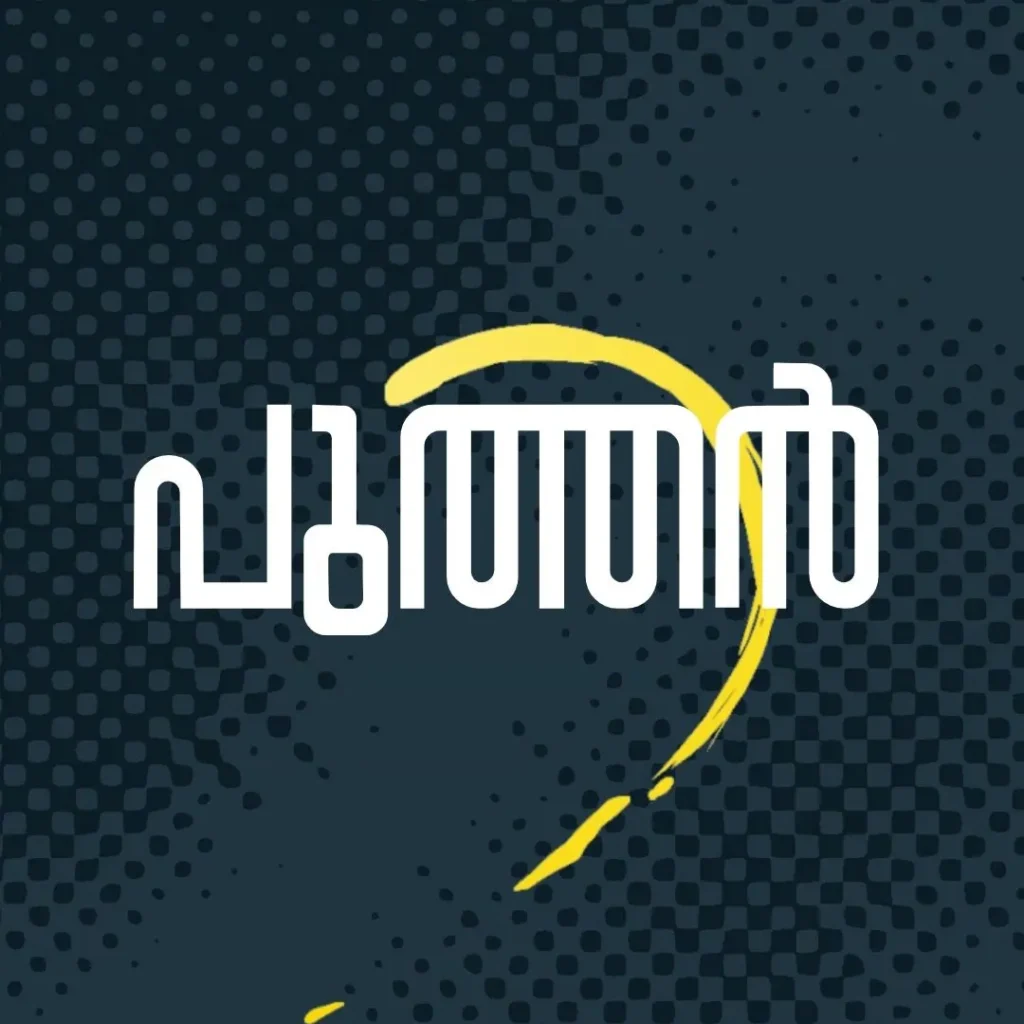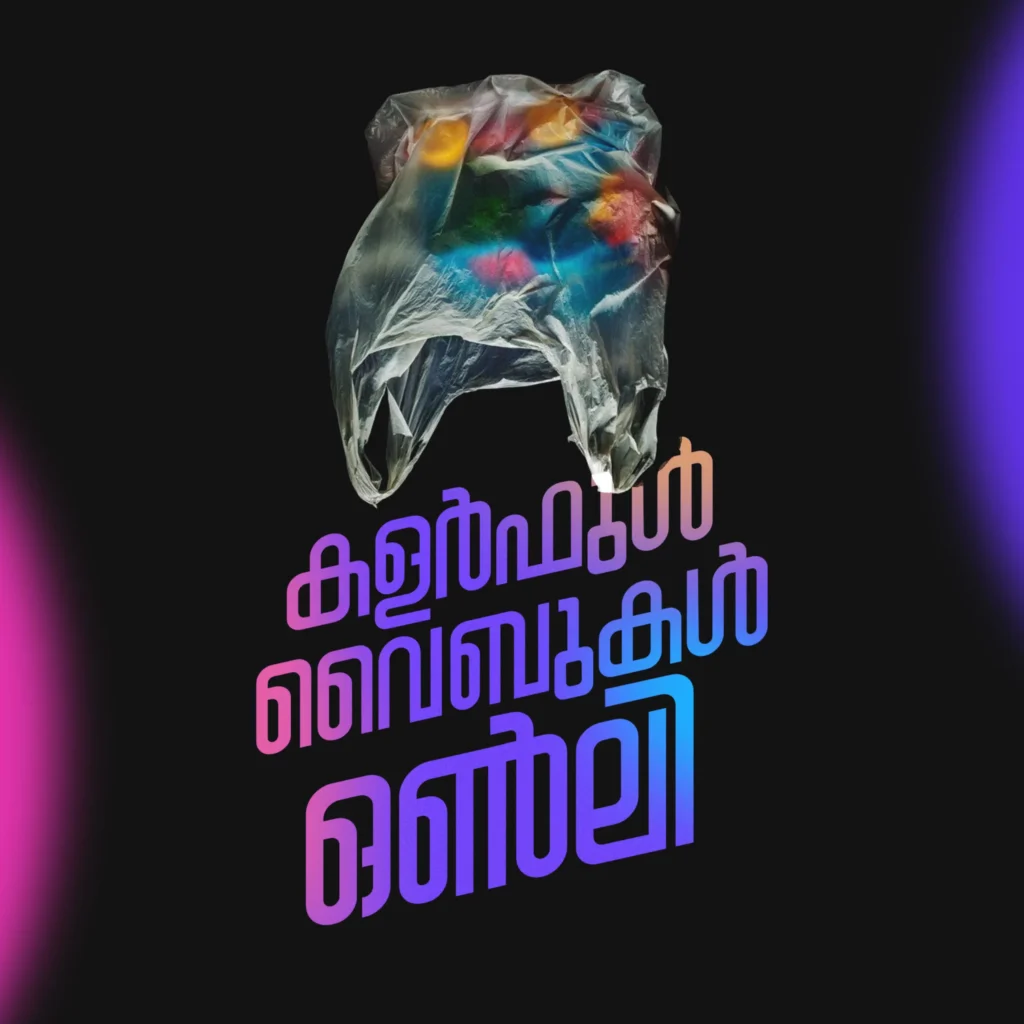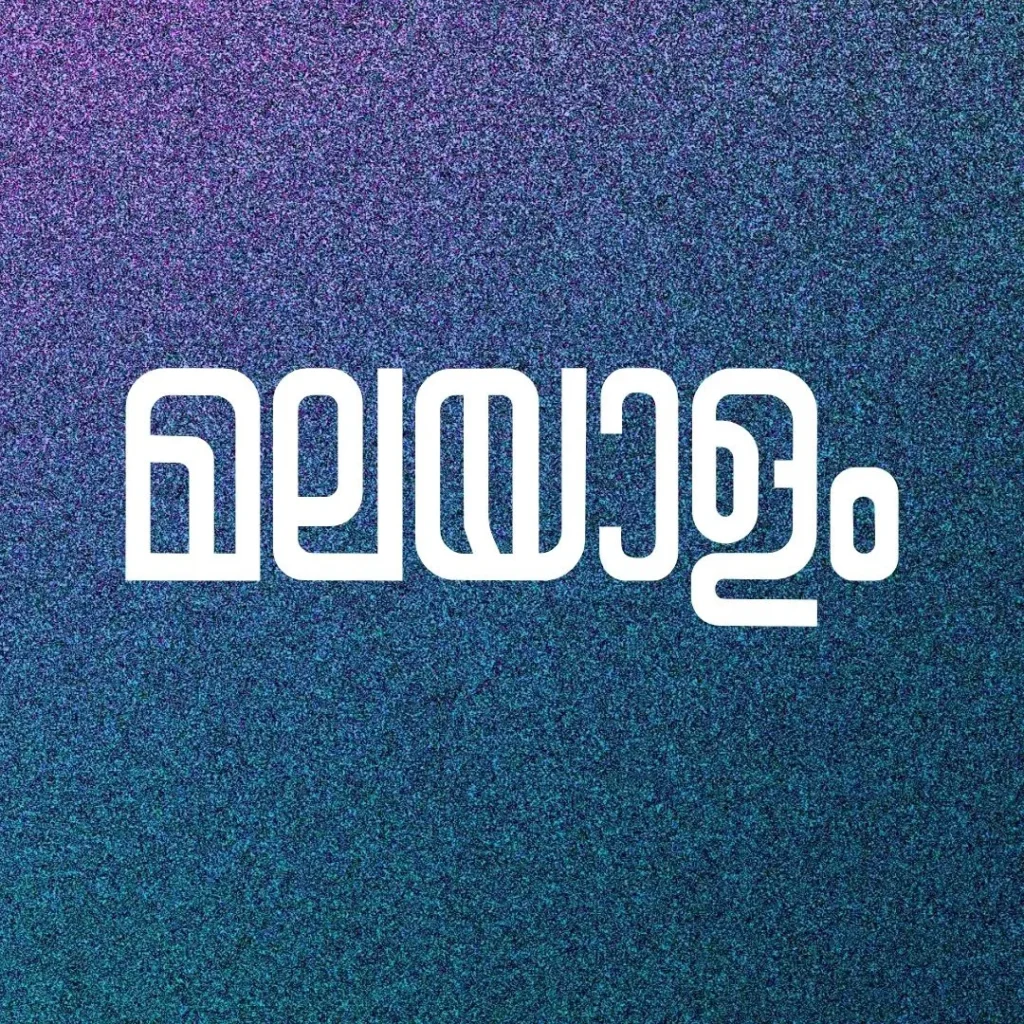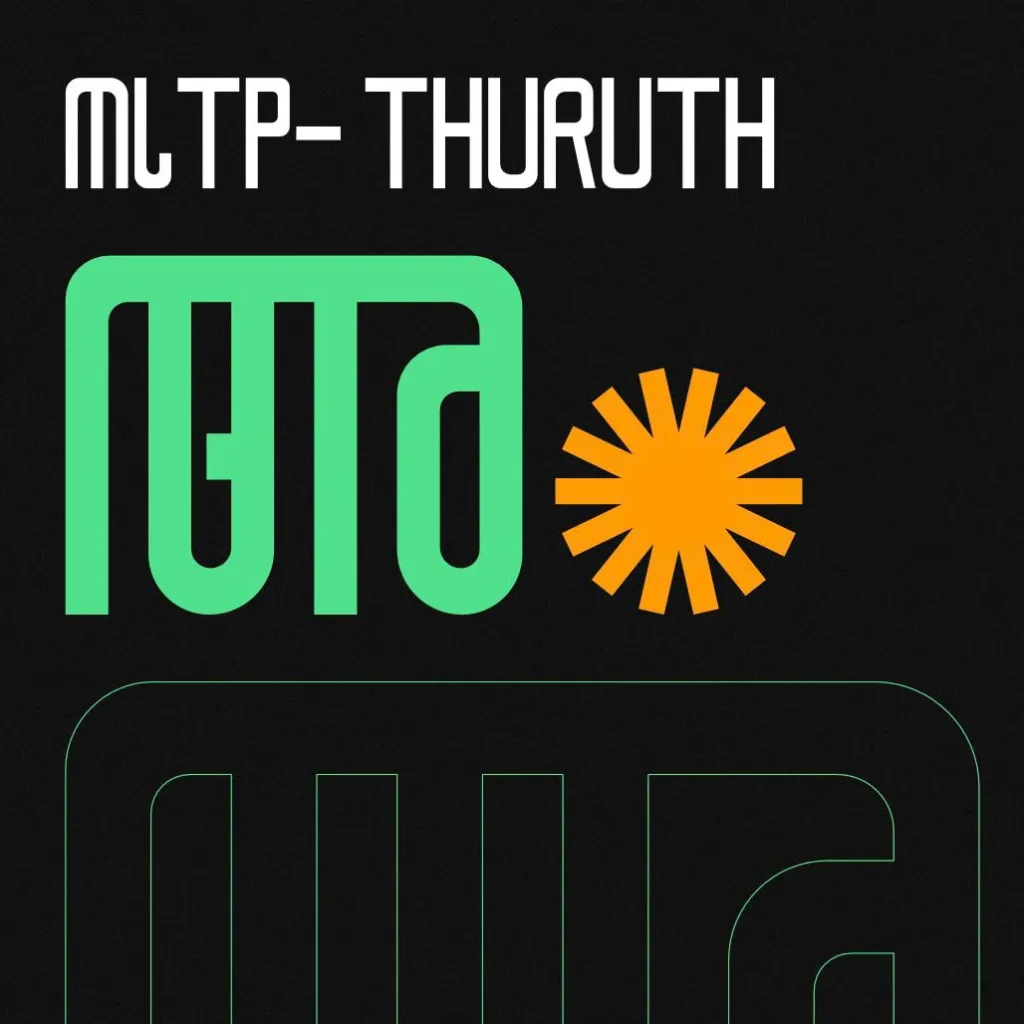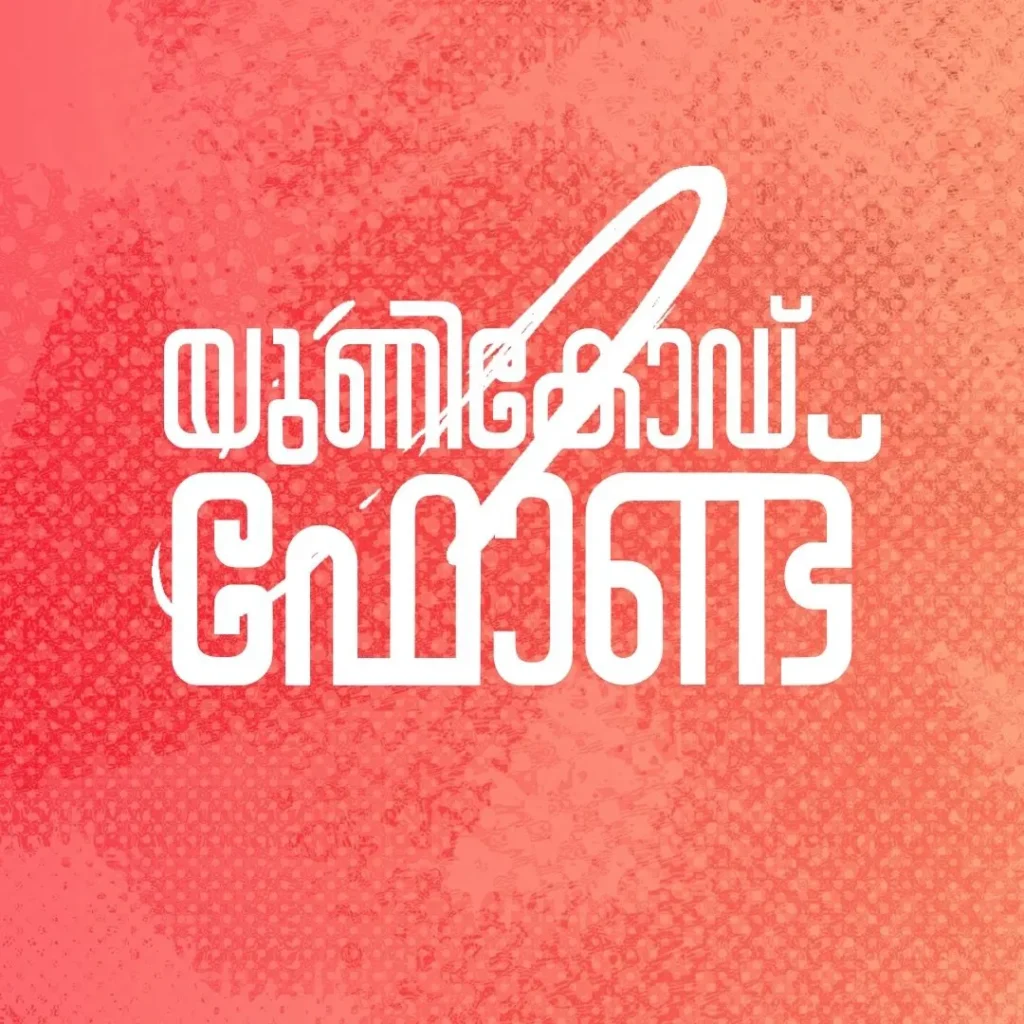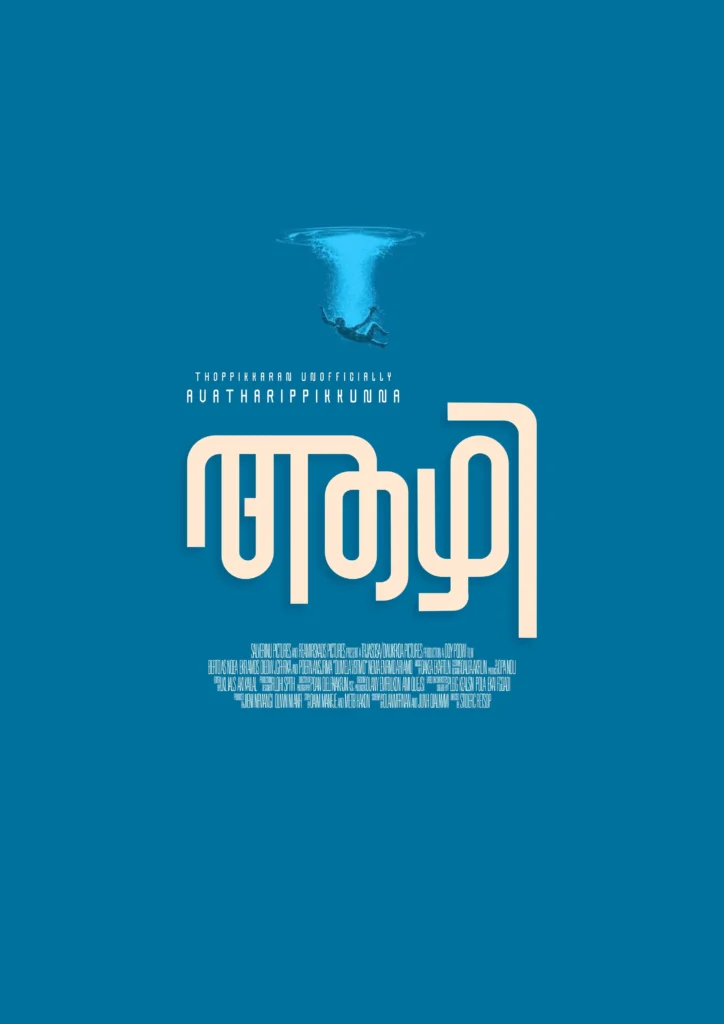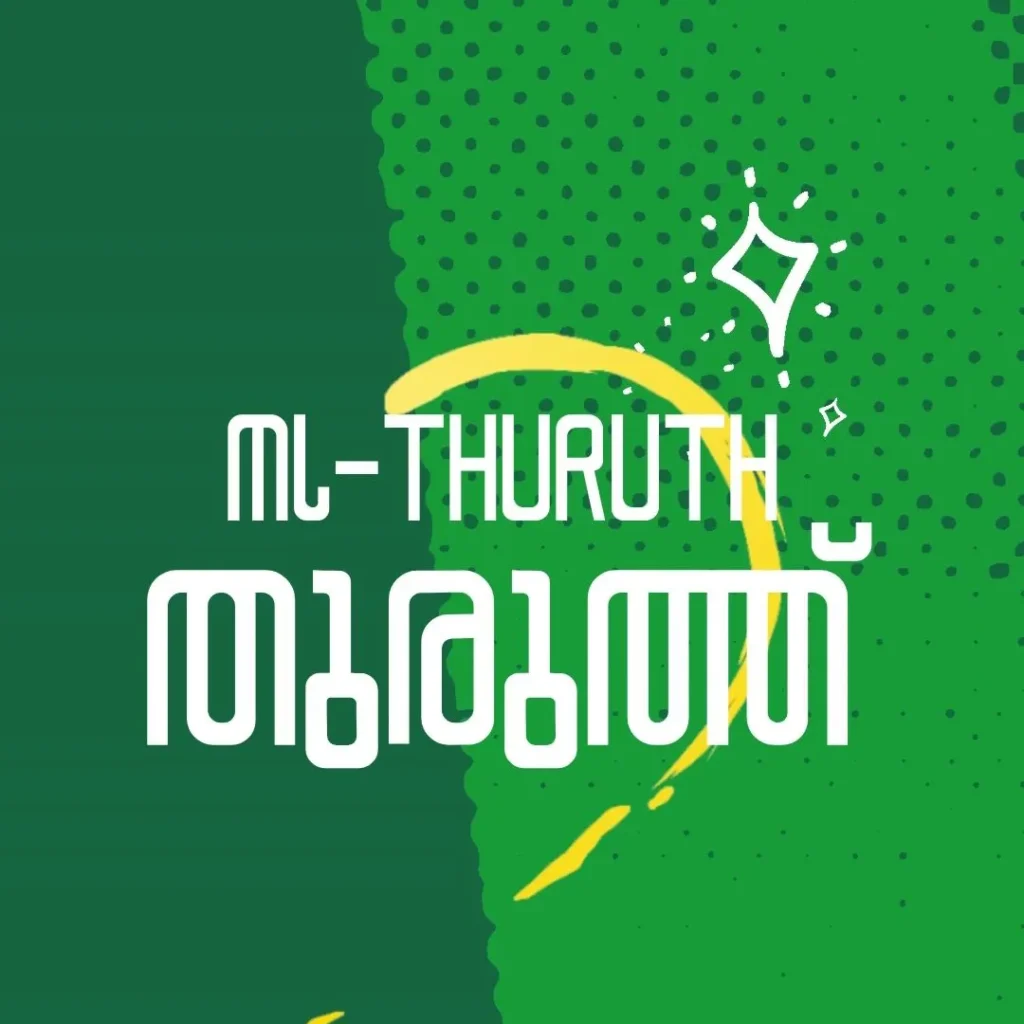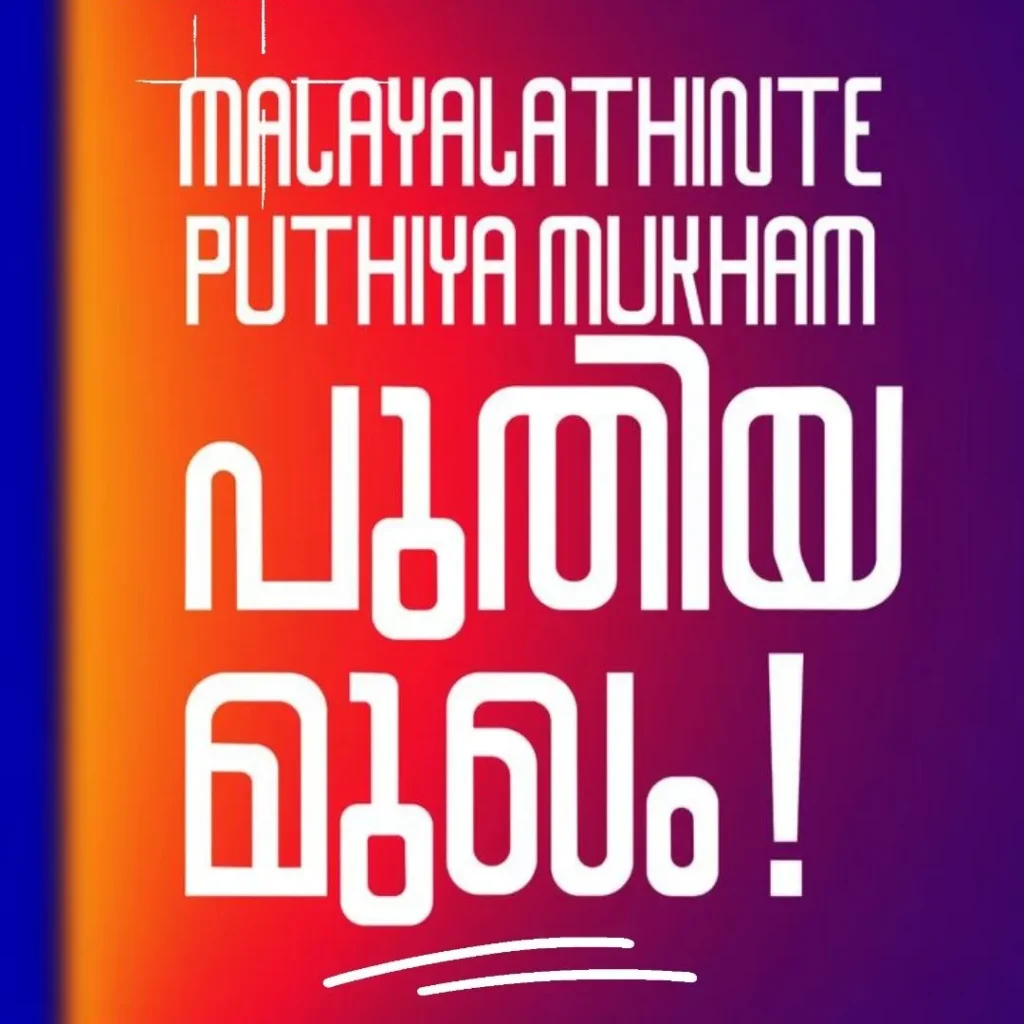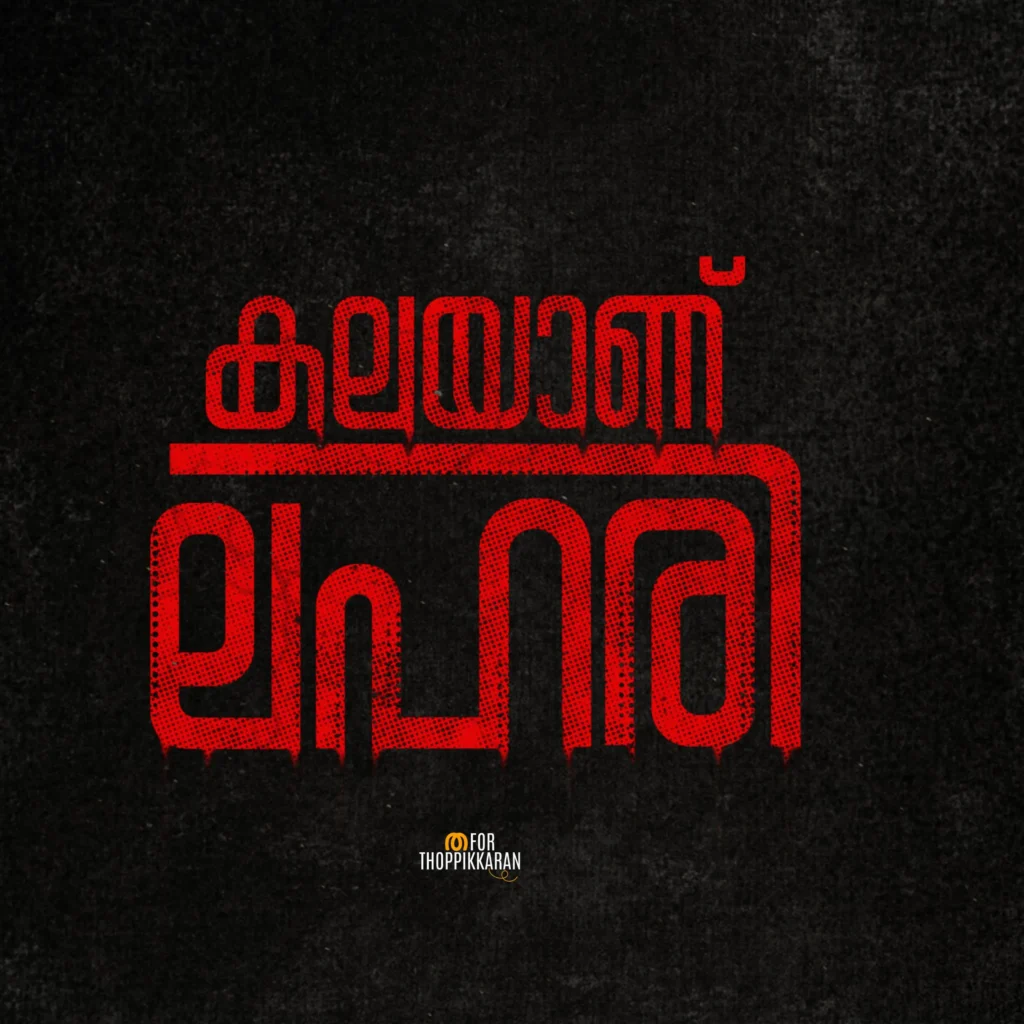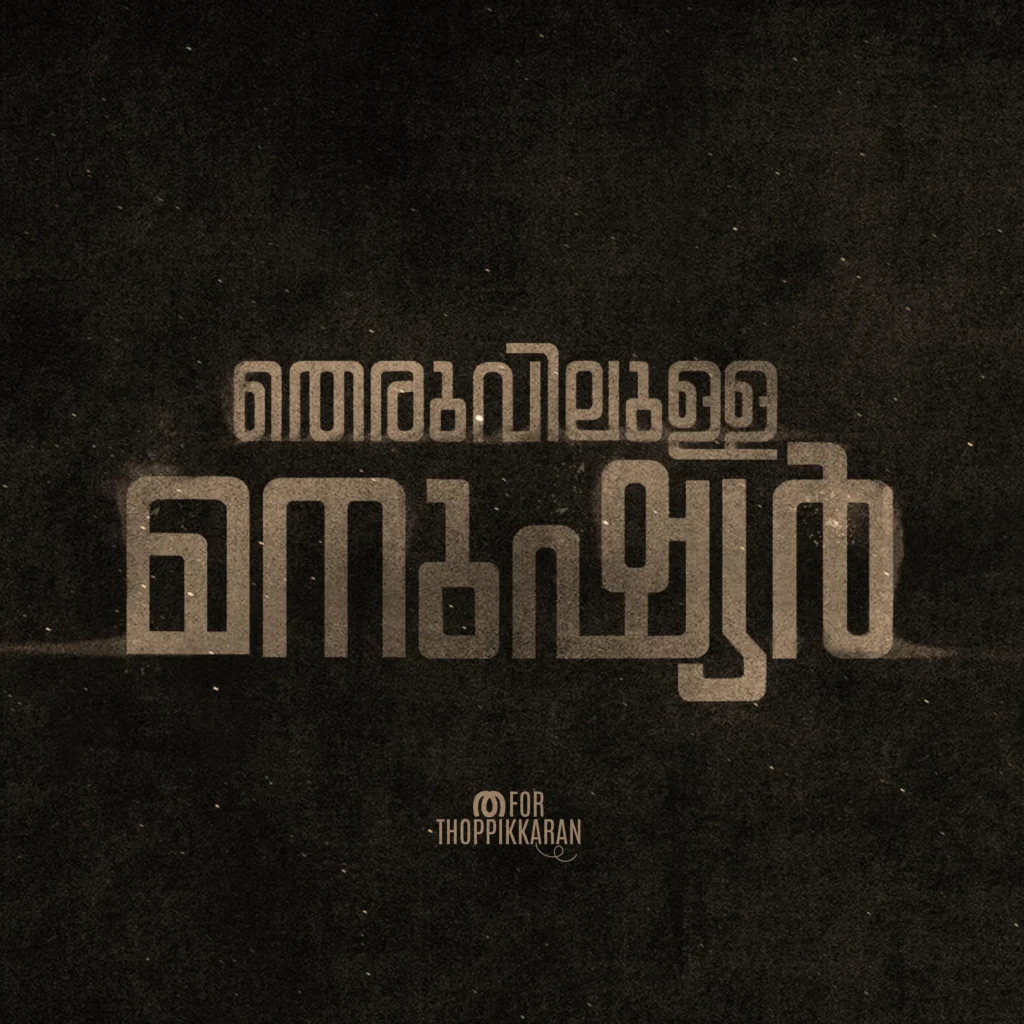
പുതിയ മലയാള ഫോണ്ട്: MLTP-THURUTH! തുരുത്ത് Malayalam Font!
മലയാളം ടൈപ്പോഗ്രാഫിയിലും ഗ്രാഫിക് ഡിസൈനിലും മാറ്റം സൃഷ്ടിക്കാൻ ഒരുങ്ങിയിരിക്കുകയാണ് പുതിയ MLTP-THURUTH ഫോണ്ട്! 🚀 മലയാളത്തിന്റെ സമ്പ്രദായിക സവിശേഷതകൾ ഉൾകൊണ്ടുകൊണ്ടു തന്നെ, ആധുനിക സാങ്കേതികതയുമായി ഒത്തിണങ്ങുന്ന ഈ യൂണിക്കോഡ് ഫോണ്ട്, ടൈറ്റിലുകൾക്കും, ക്രിയേറ്റീവ് ഡിസൈൻ പ്രവൃത്തികൾക്കും അനുയോജ്യമാണ്.
“Thuruth” എന്നത് ദ്വീപ് എന്നാണ് അർത്ഥം, അതുപോലെ തന്നെ മലയാളം ലിപിയിലേയ്ക്ക് ഒരു പുതിയ സങ്കൽപ്പം കൊണ്ടുവരാൻ MLTP-THURUTH ശ്രമിക്കുന്നു. 🔥
മലയാളം യൂണിക്കോഡ് ഫോണ്ട്
ടൈറ്റിലുകൾക്കും ക്രിയേറ്റീവ് ഡിസൈനിനും അനുയോജ്യം
പരമ്പരാഗത ശൈലിയോടൊപ്പം ആധുനിക സുന്ദരത്വം
📌 ഫോണ്ട് നിർമ്മിച്ചത്:
THOPPIKKARAN (Fazil Mukhthar)
മലയാളം ലിപിയെ സ്നേഹിക്കുന്നവർക്ക് ഈ ഫോണ്ടുകൾ ഒരു മുതൽക്കൂട്ടാണ്. മലയാളം ടൈപ്പോഗ്രാഫിയിൽ പുതിയ പരീക്ഷണങ്ങൾ നടത്താൻ ആഗ്രഹിക്കുന്നവർക്ക് ഈ ഫോണ്ടുകൾ ഉപയോഗപ്രദമാകും.
MLTP-THURUTH is a Malayalam Unicode font designed with a distinctive and creative approach for typography and graphic design purposes. The name”Thuruth” translates to “island” in Malayalam, symbolizing a unique and
isolated space, which the font aims to represent in typography. This font is crafted to capture the traditional nuances of the Malayalam script while offering a fresh, artistic touch suitable
for modern design contexts.